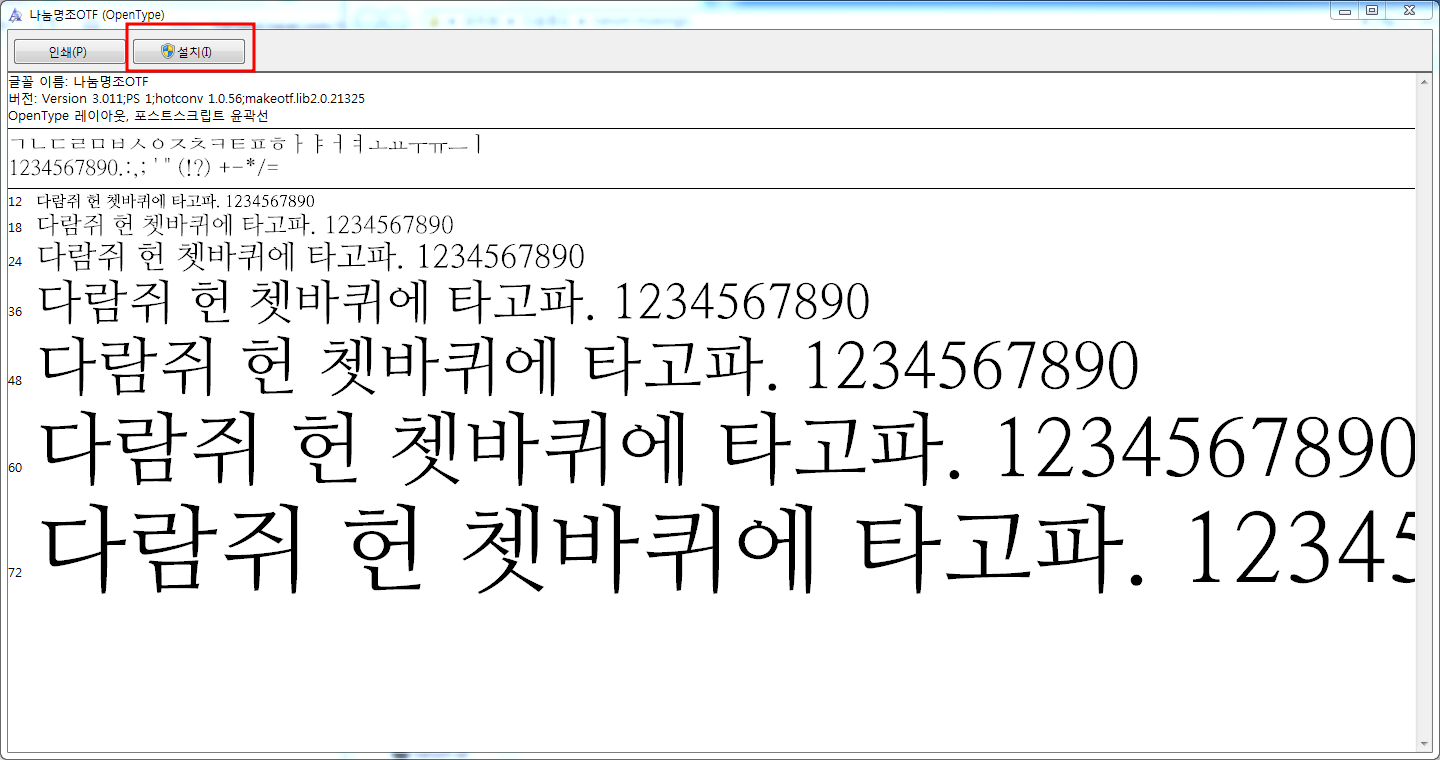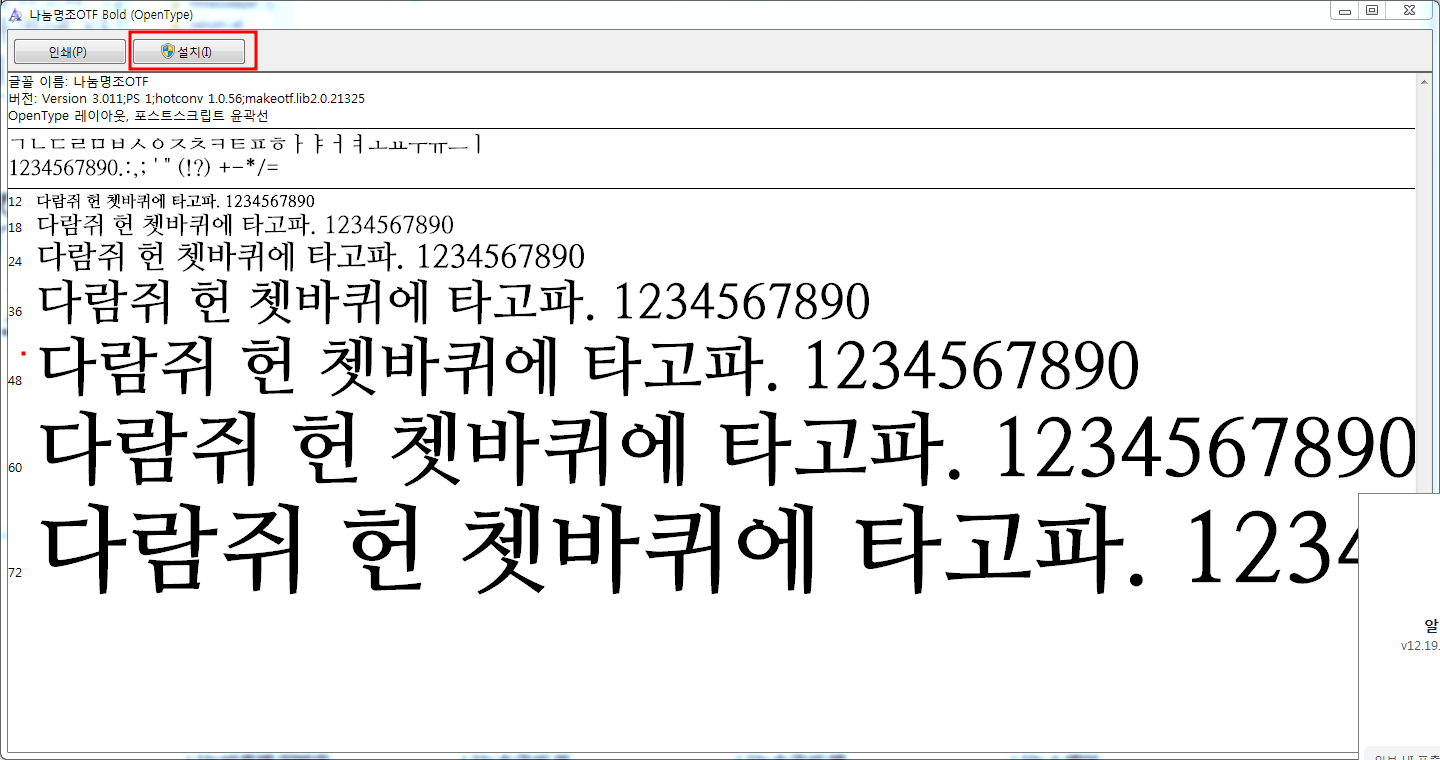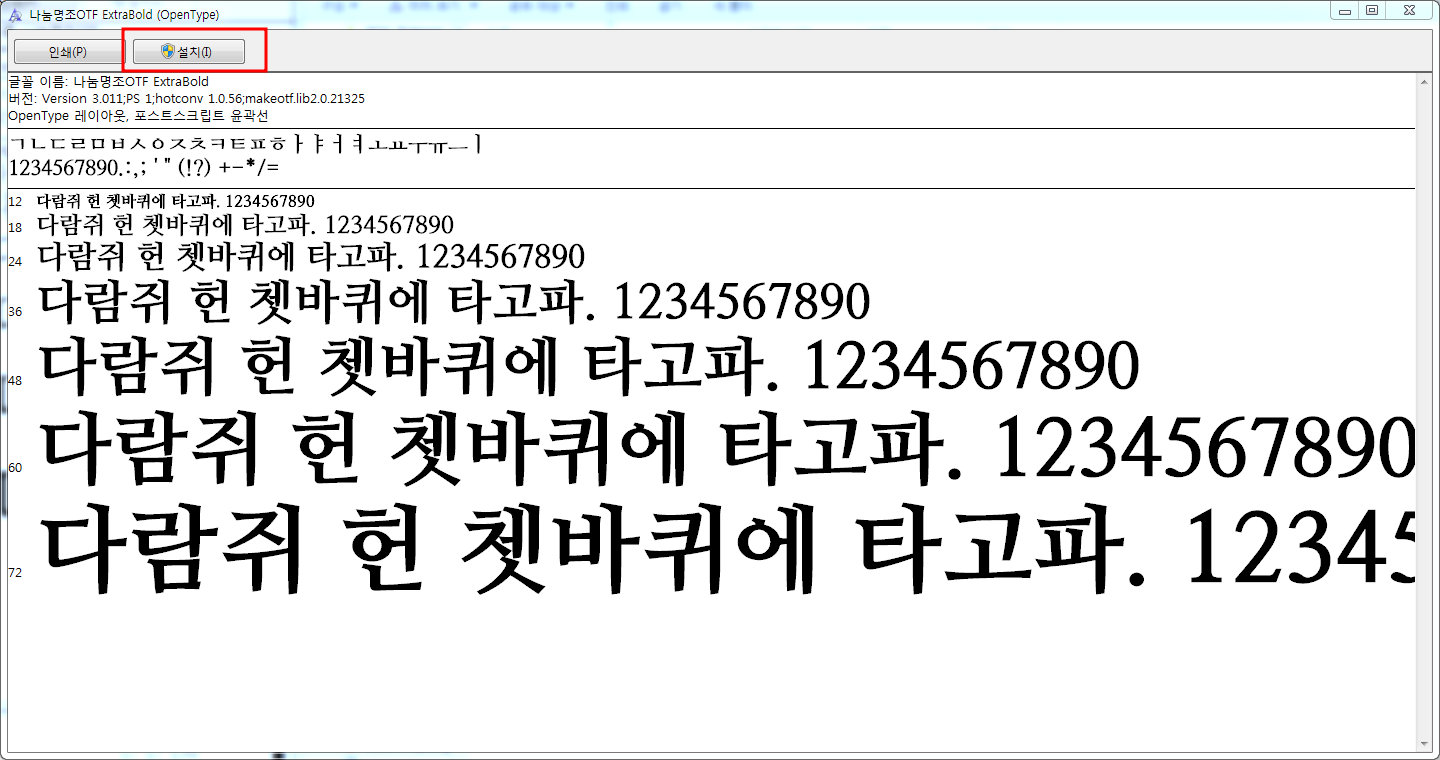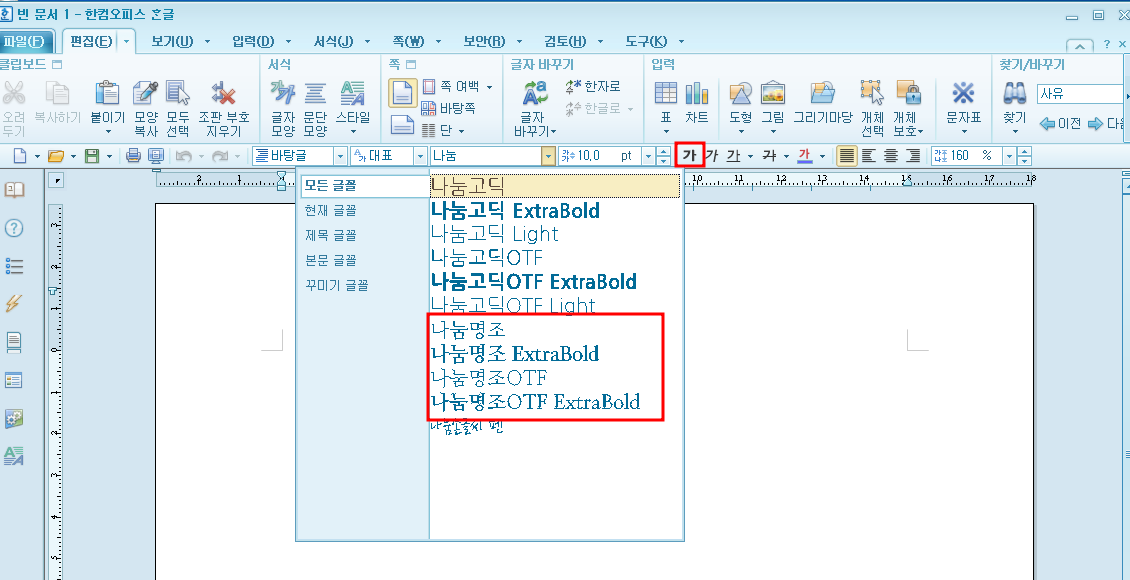
나눔고딕과 함께 문서 만들 때 많이 사용되고 있는 나눔명조는 네이버에서 무료로 배포한 폰트라는 사실 알고 계셨나요? 나눔명조는 나눔고딕과 마찬가지로 상업적으로도 사용이 가능한 무료 폰트입니다. 개인 및 기업 사용자도 모두 사용할 수 있고 글자체 간결하기 때문에 문서 작성 시 해당 폰트를 한번 사용해 보시는 것을 추천드려요. 직장인들이 사랑하는 나눔명조, 나눔명조 Bold, 나눔명조 ExtraBold 폰트 다운로드 방법과 설치방법에 자세하게 알아보겠습니다.
4. 나눔명조 Bold OTF 설치창입니다. 나눔명조 글자체보다 굵은 것을 확인할 수 있습니다. [설치]를 클릭하여 폰트를 설치합니다.
5. 나눔명조 ExtraBlod도 동일하게 [설치]를 클릭하여 설치해 주세요. 아주 굵은 글씨체로 제목에 알맞겠네요.